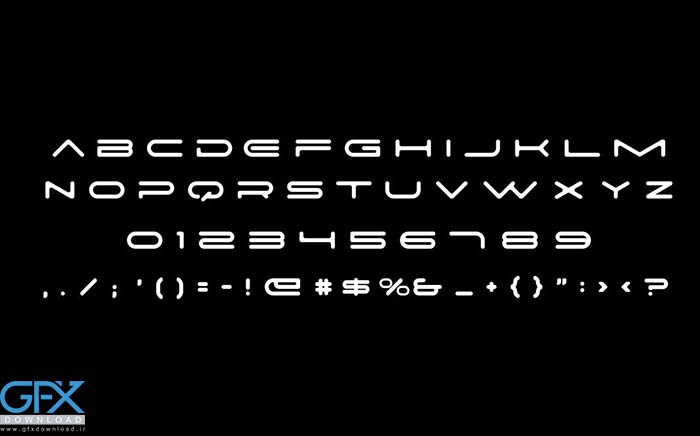
دانلود رایگان فونت Avonger
دانلود فونت Avonger
دانلود رایگان فونت انگلیسی Avonger
فونت Avonger یک فونت مدرن و نمایشگر برجسته و معتبر است. این فونت برای هر پروژه برندسازی مانند لوگو، چاپ تی شرت، esport و بسیاری موارد دیگر مناسب است. دانلود رایگان فونت Avonger مناسب در طیف گسترده ای از زمینه ها.
فونت رایگان Avonger